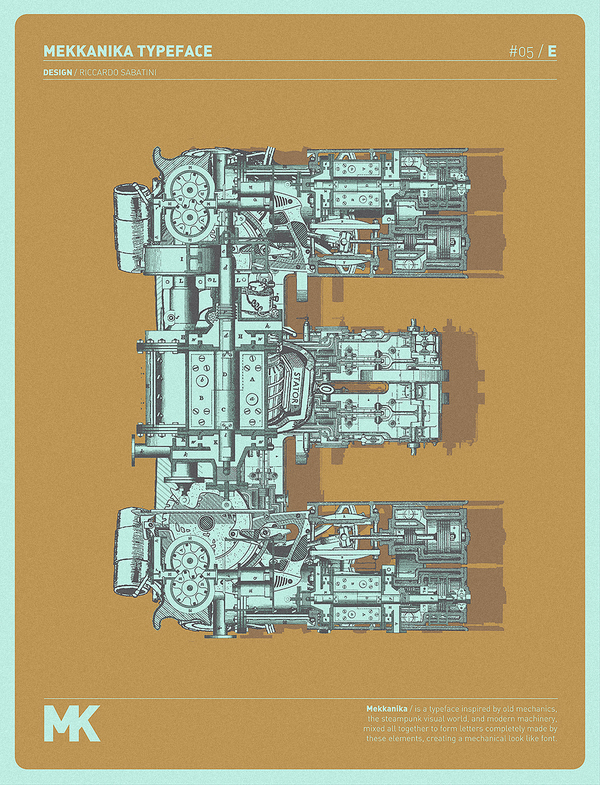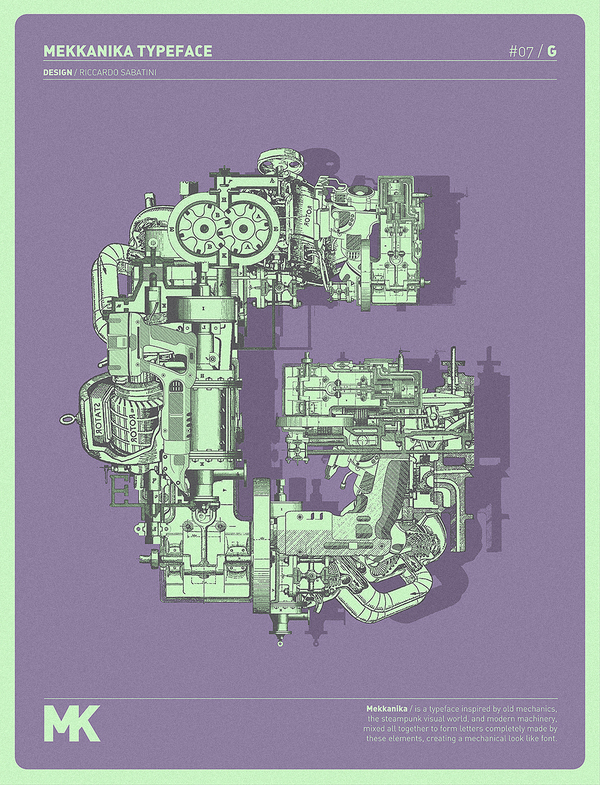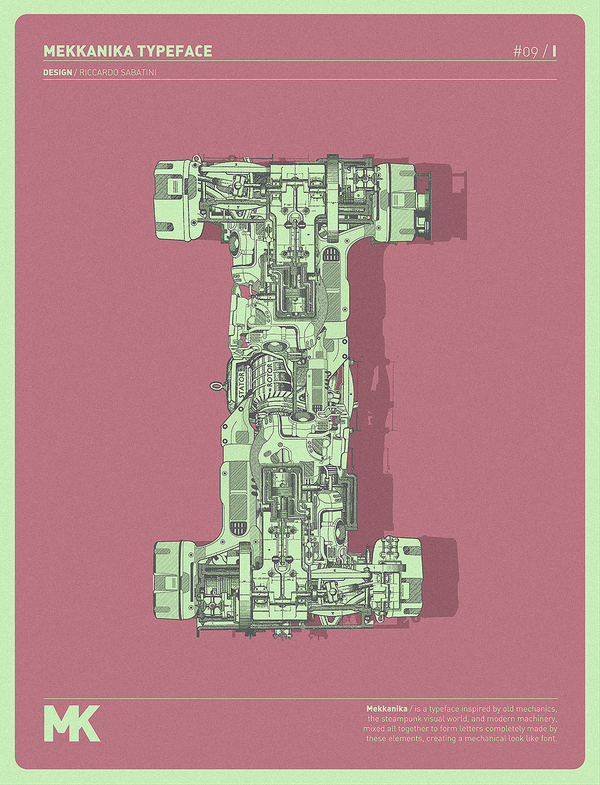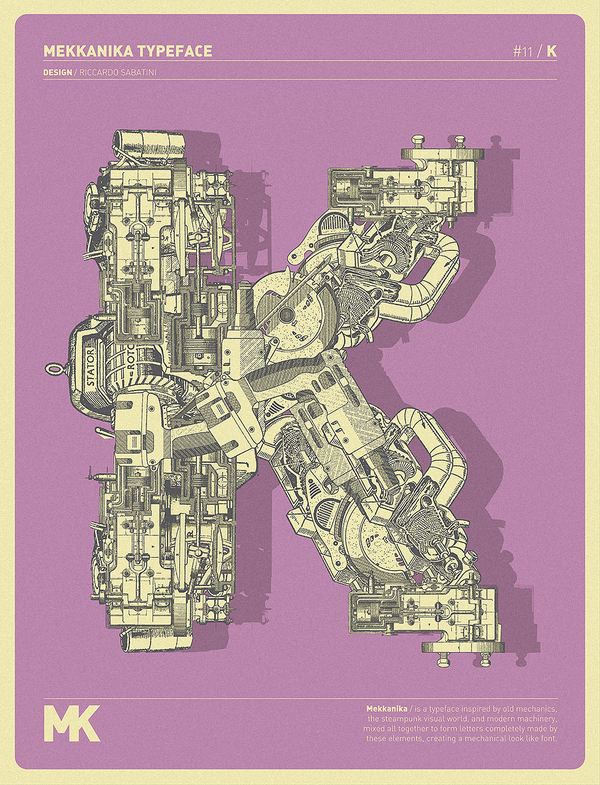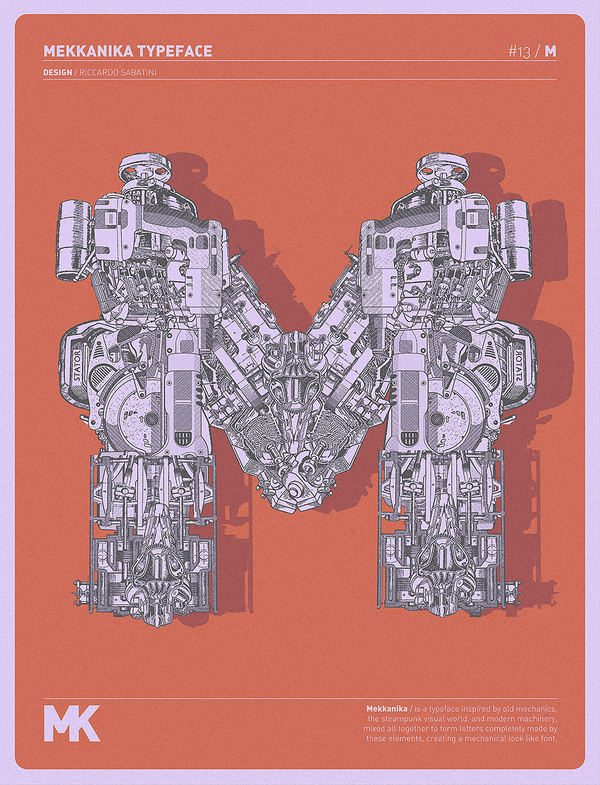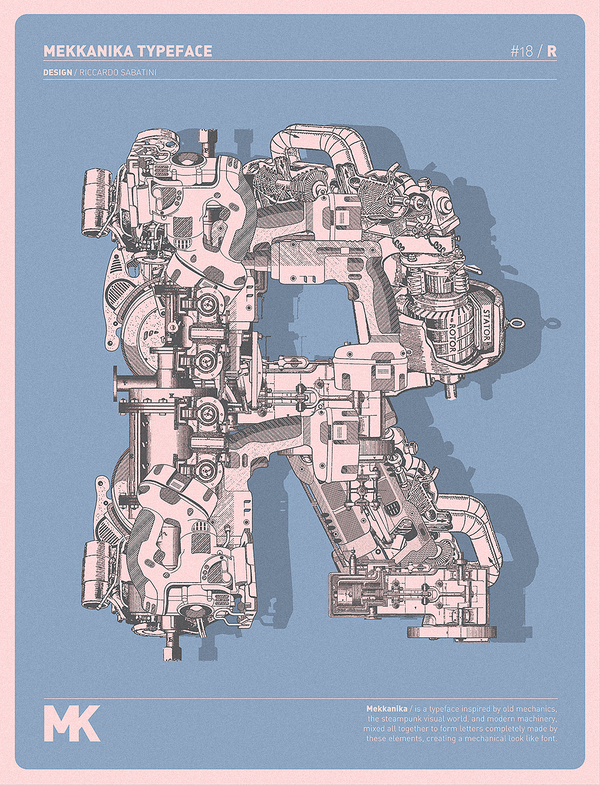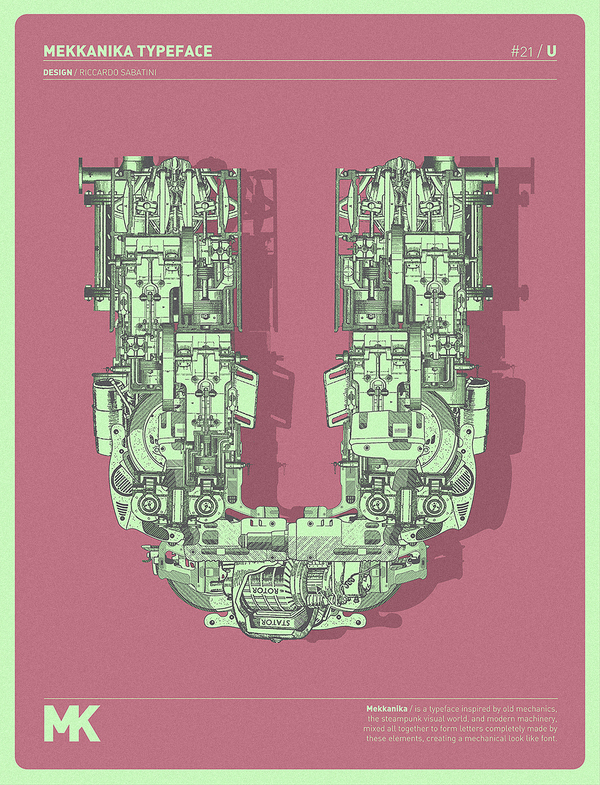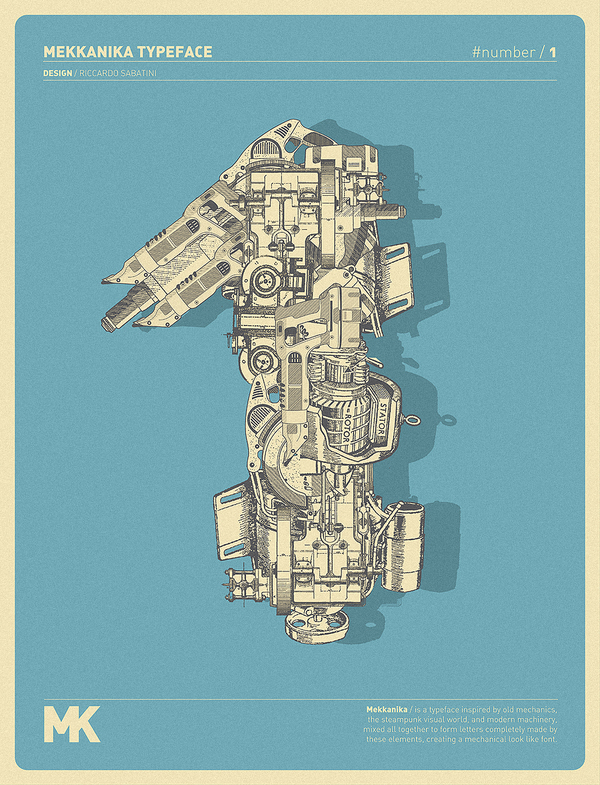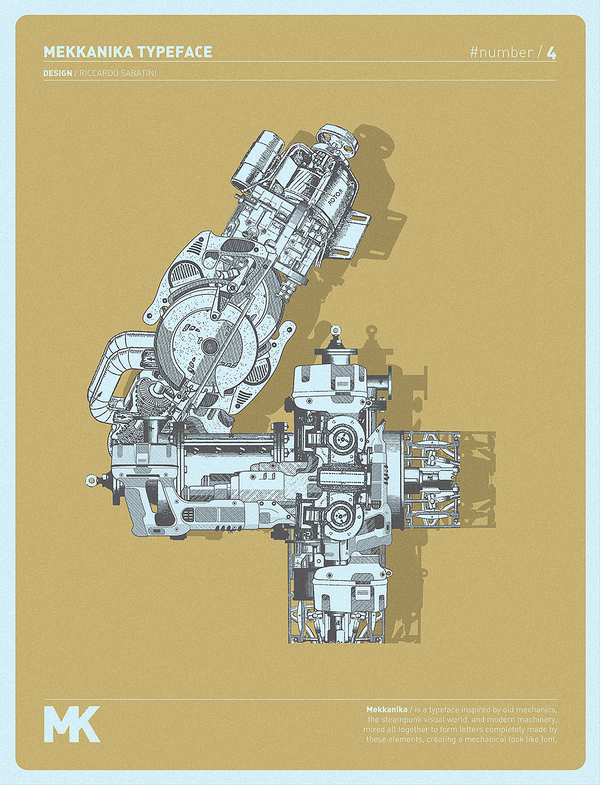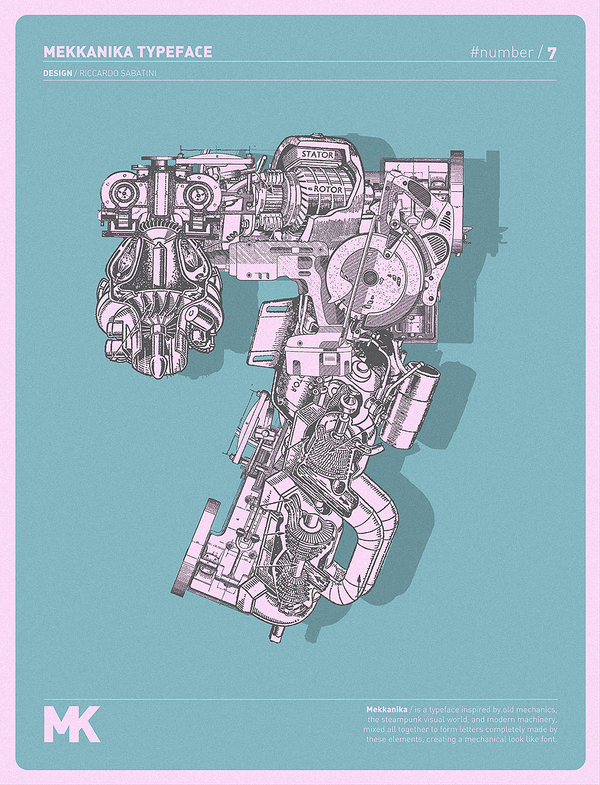
Mekkanika Typeface / Riccardo Sabatini
Une création typographique expérimentale par Riccardo Sabatini.
Un design de caractère inspiré des vieilles techniques de dessins mécaniques.